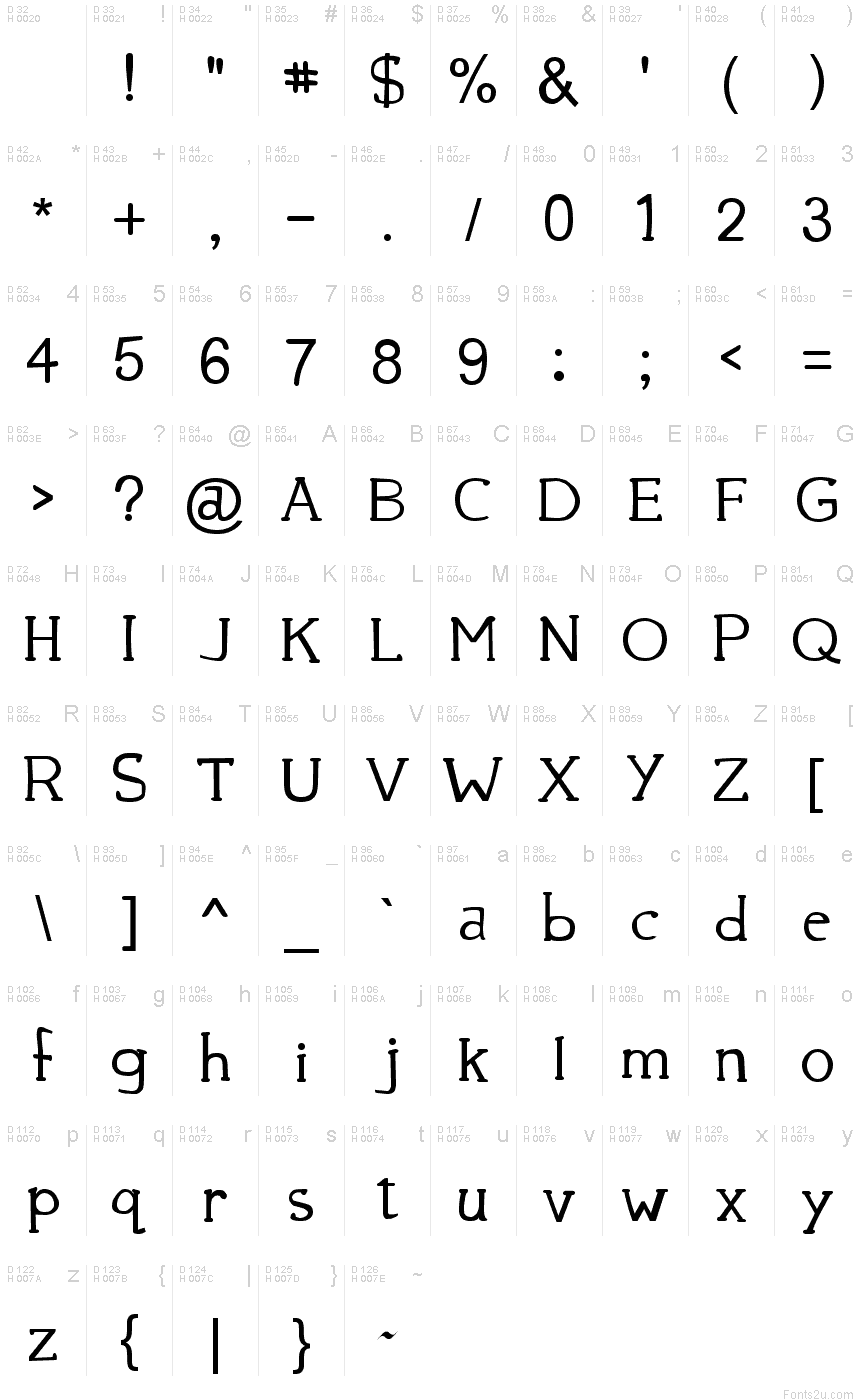
„39 Smooth“ je podmanivé displejové písmo z dílny Lauren Ashpole. Jeho výrazně zkreslená estetika jej odlišuje od ostatních a evokuje pocit dynamického pohybu a nekonvenční elegance.
Nerovnoměrné, vlnité tvary písmen vytvářejí působivý vizuální dojem, díky čemuž je toto písmo ideální volbou pro nadpisy, loga a grafické prvky, které mají zaujmout. Jeho odvážná a expresivní osobnost se skvěle hodí pro širokou škálu využití, od redakční sazby až po branding a reklamní kampaně, kde je žádoucí vytvořit jedinečný a zapamatovatelný typografický statement. Díky své všestrannosti umožňuje „39 Smooth“ designérům zkoumat jeho potenciál v digitálních i tištěných médiích a povýšit projekty o nádech neotřelého stylu.